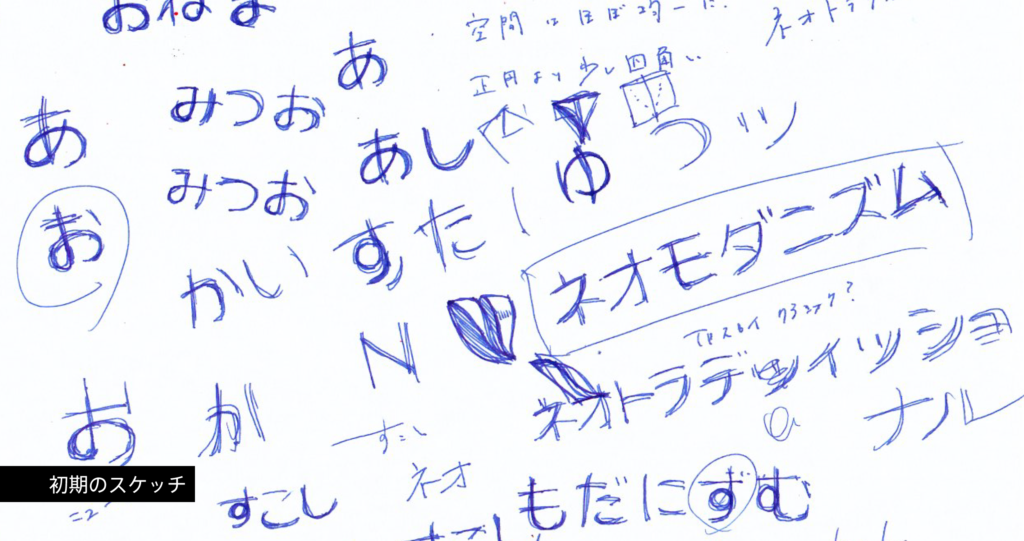
TPスカイ モダン Blk 開発ストーリー 01「モダン?」
私がTPスカイ モダン Blkに参加したばかりの頃によく考えていたのは「“モダン”ってなんだろう?」ということです。ひらがなや欧文の試作は既に出来ていて目指すところは示されていたのですが、それでも担当することになった漢字やカタカナをカタチにしていく上で“モダンな和文書体”のイメージが自分には足りないと感じていました。
というのは、デザイン・文字業界にモダンスタイルとカテゴライズされる和文書体が出始めた頃の衝撃や流行の話は見聞きしていたものの、自分自身は当時まだ生まれていないか赤ちゃんの頃なので個人的にモダンには「体験しそびれたもの」という印象があったのです。そこで、その見聞きしていた和文書体を調べるのはもちろん、欧文書体や建築・アート・ファッションなどの分野からもモダンを捉えようとしてみました。私はよく作業中に音楽を聞いているのですが、当時はTPスカイ モダンが似合いそうな曲を選んだりもしていました。
モダンのイメージが少しずつ入ってくるのと同時に「リバイバル的な流行」「多様化する社会」といった体験しているキーワードも合わさってきて、このモダンはきっと「これからの活躍する”モダン”」なのだろう、と完成したフォントを使ってもらえるシーンが想像できるようになりワクワクしたのを覚えています。